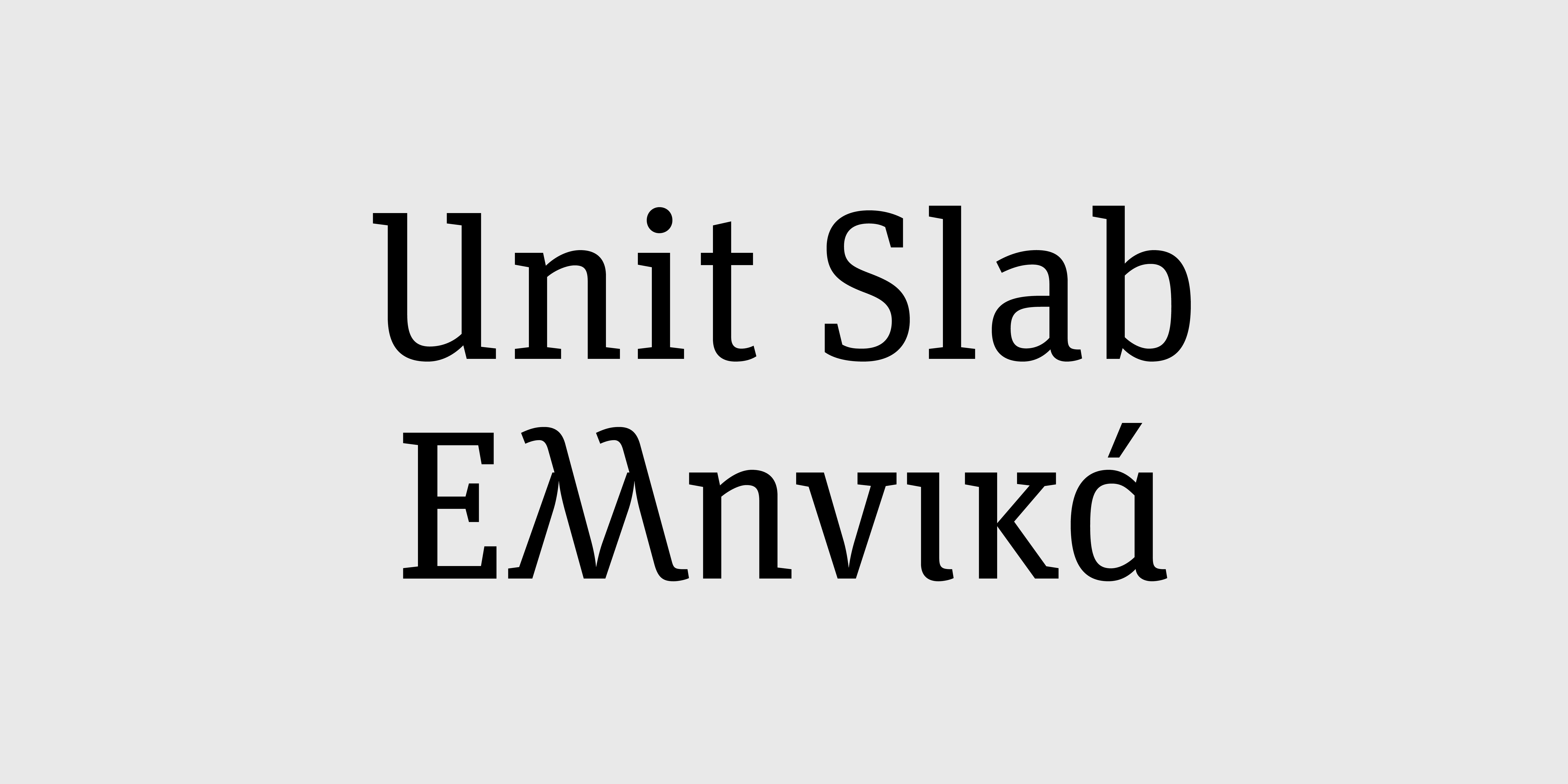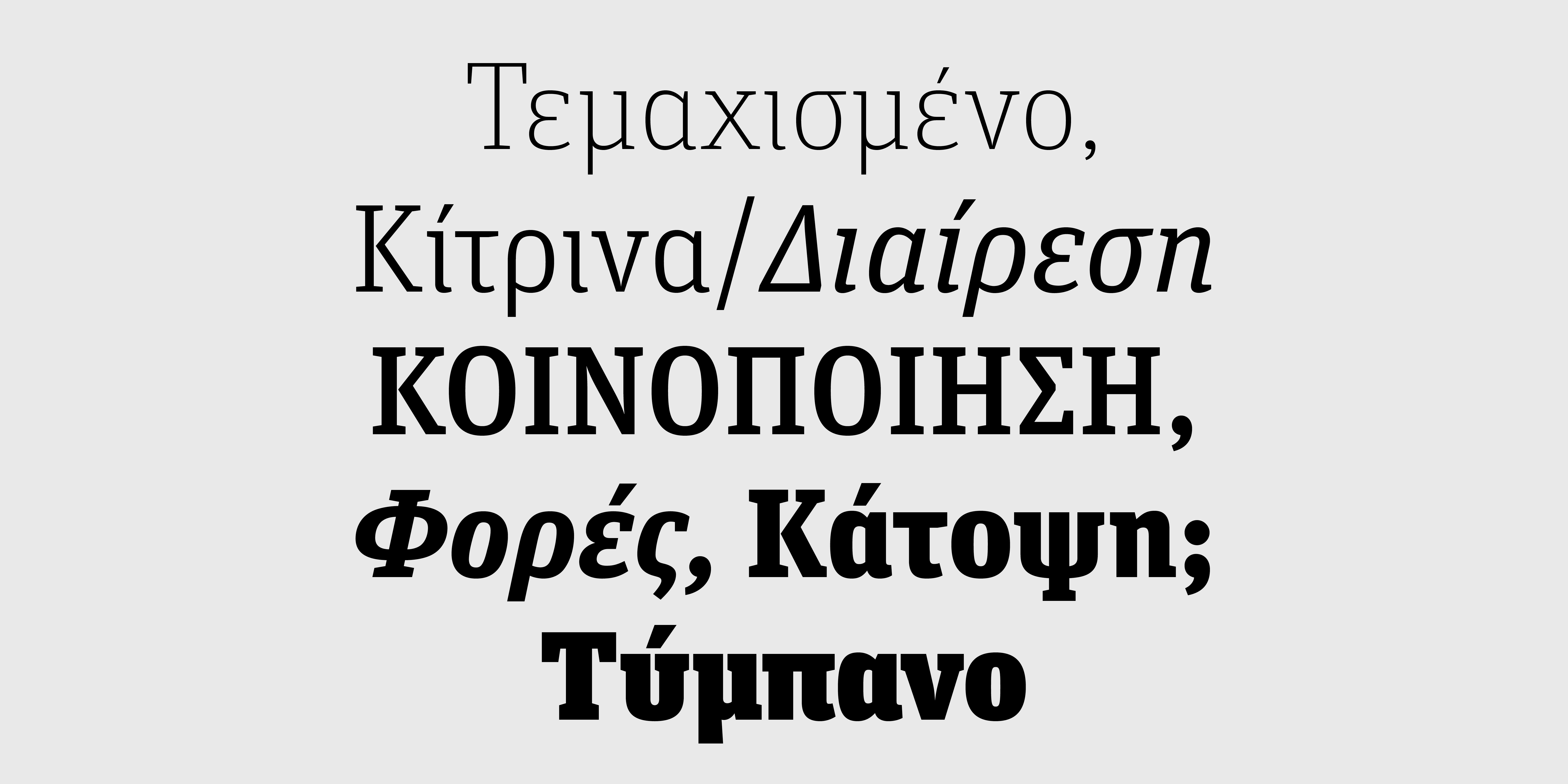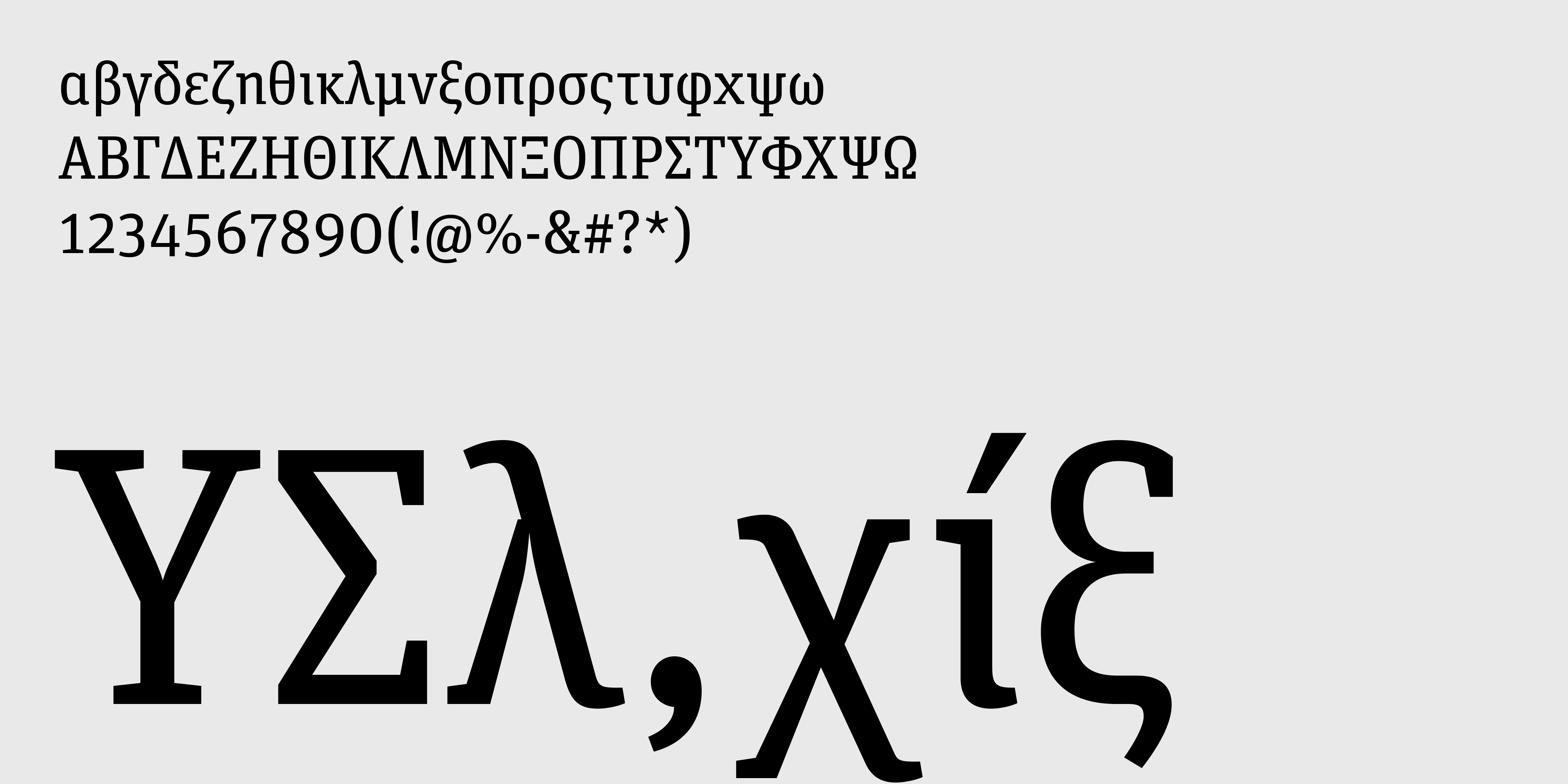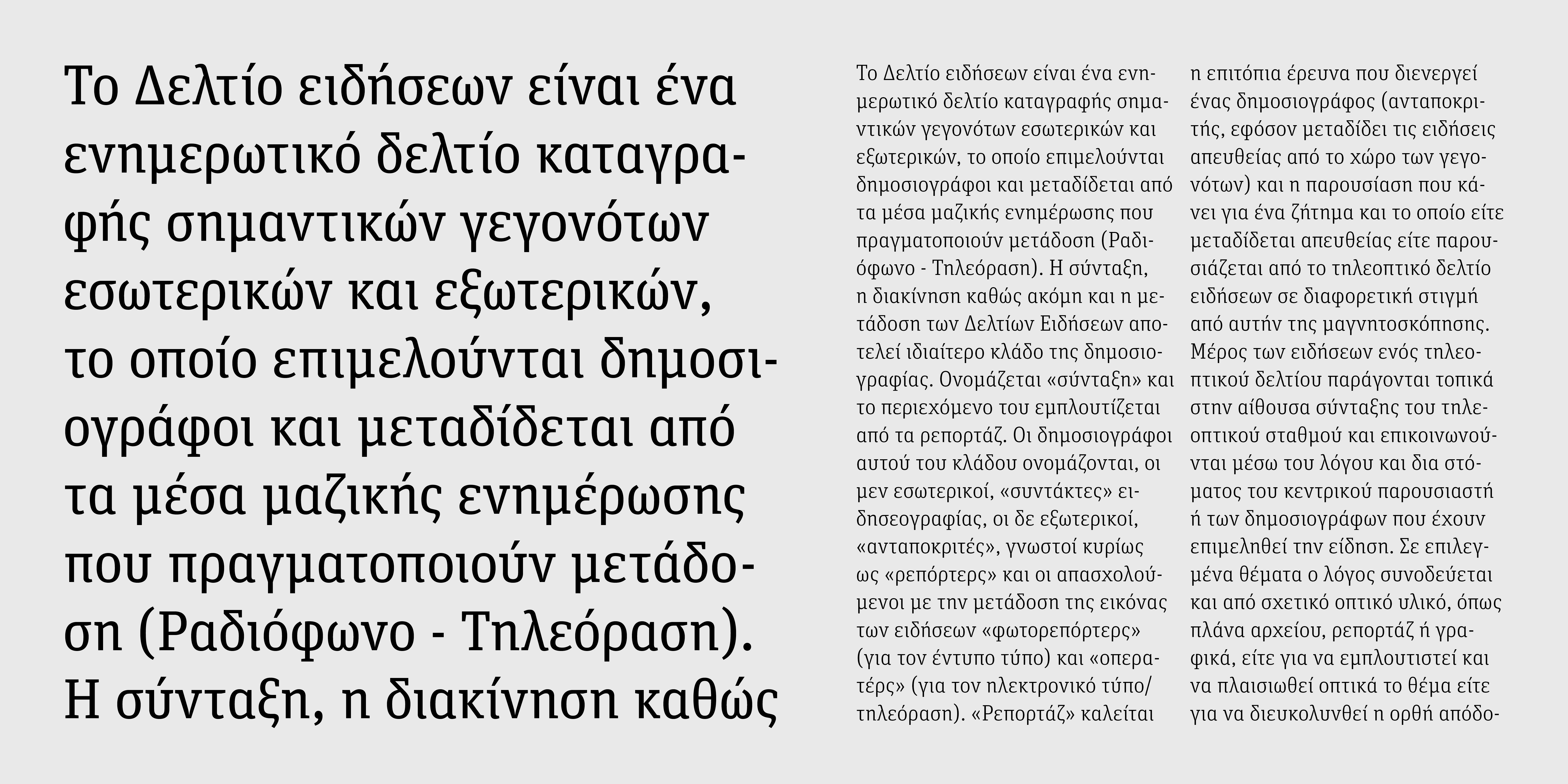
Unit Slab Pro Collection
Unit Slab 1 Pro
Light Light Italic Regular Italic Medium Medium Italic Bold Bold ItalicUnit Slab 2 Pro
Thin Thin Italic Black Black Italic Ultra Italic UltraΕίναι μια σχετικά στενή ανισόπαχη γραμματοσειρά με χοντρές, τετράγωνες (Slab) πατούρες. Ιδανική για τίτλους αλλά επίσης πολύ καλή και για κείμενο, αφού είναι μεν γεωμετρική αλλά συνδυάζει ανθρωπιστικά στοιχεία σχεδιασμού. Περιλαμβάνει λατινικούς, ελληνικούς και κυριλλικούς χαρακτήρες υποστηρίζοντας πάνω από 70 γλώσσες ενώ διαθέτει πολλούς διαφορετικούς τρόπους αρίθμησης. Τα ελληνικά αρχικά σχεδιάστηκαν για την εφημερίδα «ΜΕΤΡΟ».